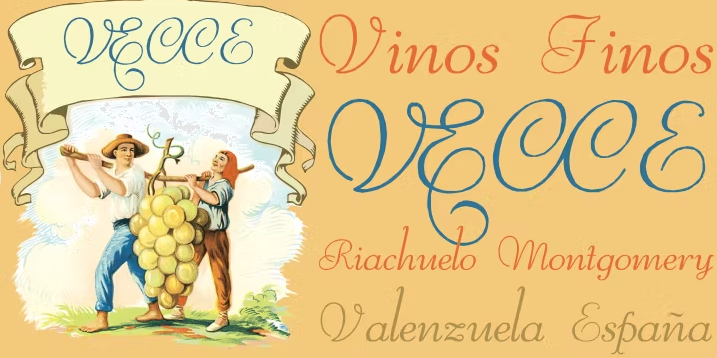
Reliant - это свободная интерпретация классического дизайна из шрифтов “BernhardSchoenschrift”, первоначально разработанная Люсьеном Бернхардом и “Liberty”, разработанная В.Т. Сниффином для ATF в 1927 году, следуя оригинальным проектам Люсьена Бернхарда.
Эта улучшенная версия OpenType имеет полные наборы на греческом и латинском алфавите с полными ресурсами Центральной Европы, Вьетнама, Балтии и Турции со всеми диакритическими знаками пунктуации плюс дополнительные символы, принадлежащие этим диапазонам.
Завершает шрифт кириллица, и мы благодарим Дмитрия Грешнева из Green Type. Он помогает нам зафиксировать наш оригинальный кириллический алфавит для читателей на кириллице.
Мы добавили обширный набор лигатур (стилистические и контекстные альтернативные варианты плюс дискреционные лигатуры), предоставляя множество вариаций формы букв, которые делают ваш дизайн действительно особенным, плюс свахи и хвосты орнаментов (для художественного увеличения любой буквы этого шрифта) больше дробей и числовых лигатур (странная идея из Иза W). Более 800 глифов, к которым у вас есть полный доступ, используя программное обеспечение, такое как InDesign, Illustrator, QuarkXpress и другие.